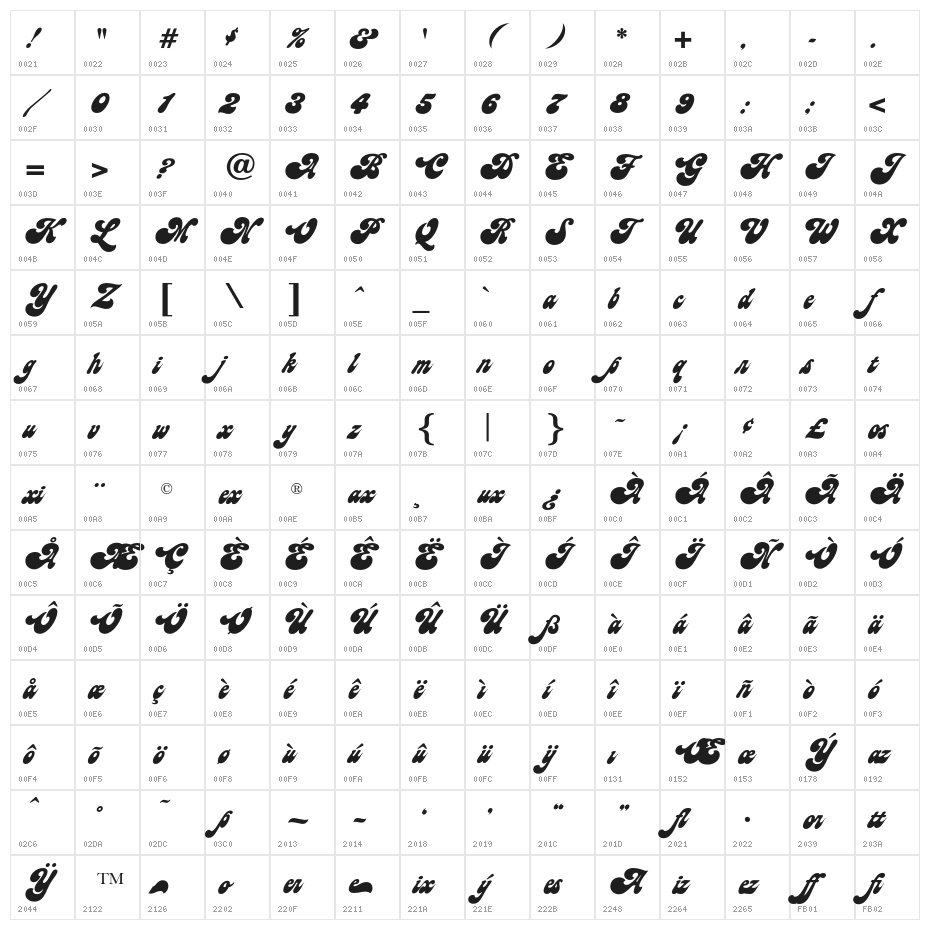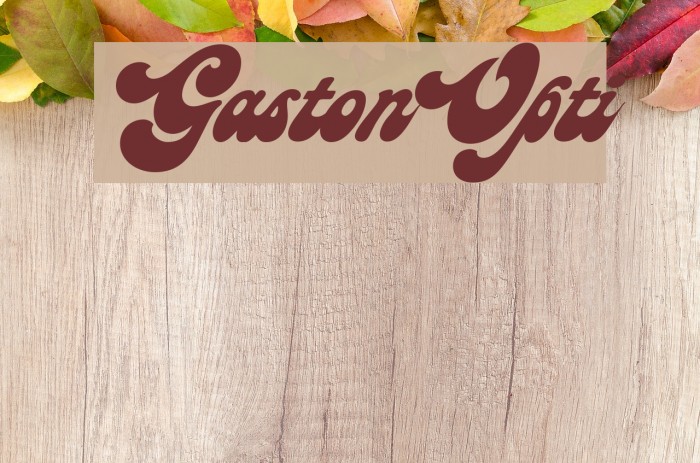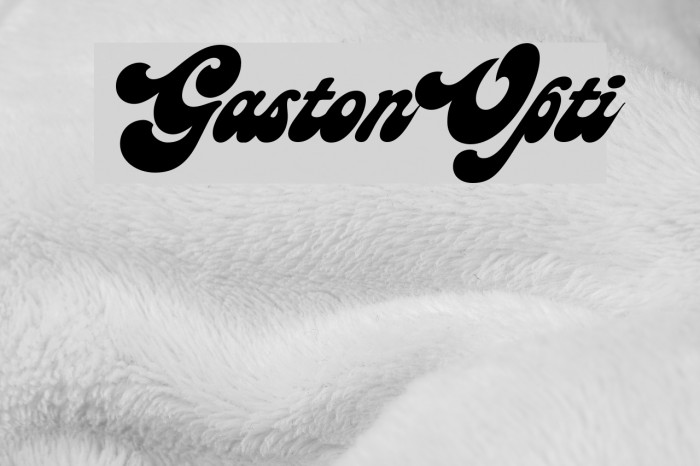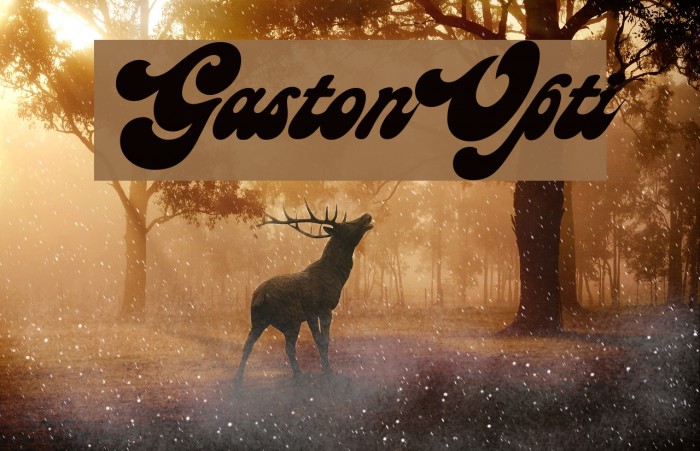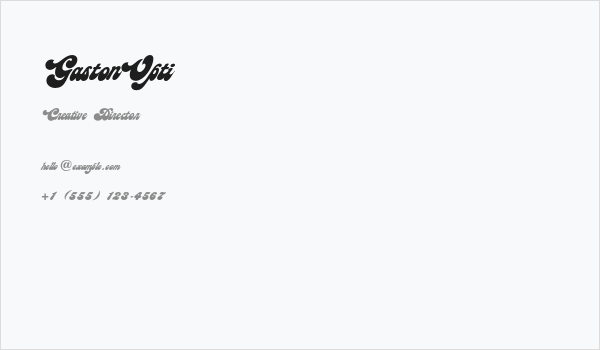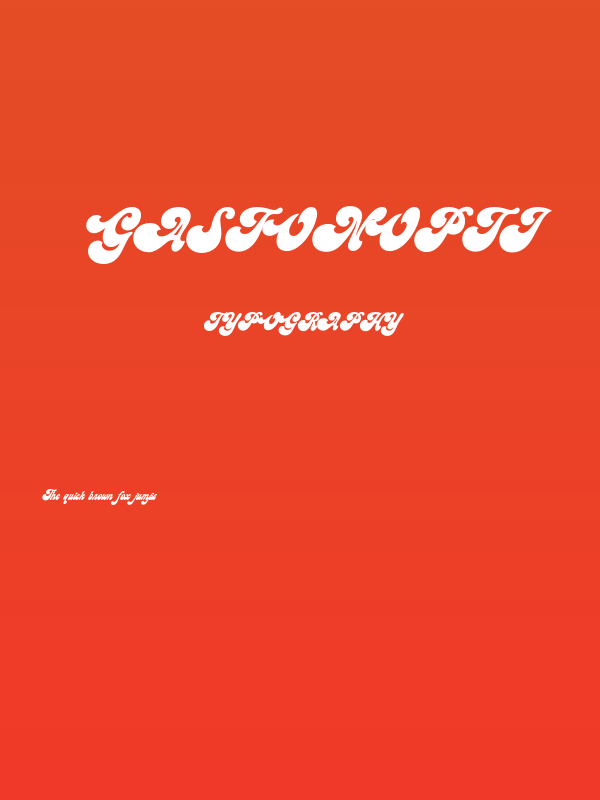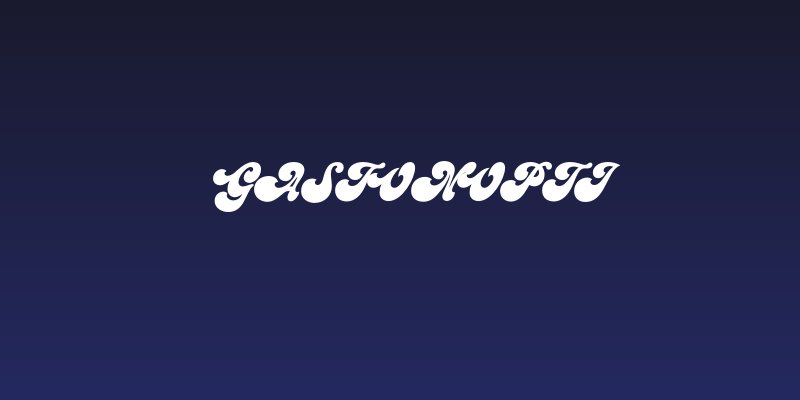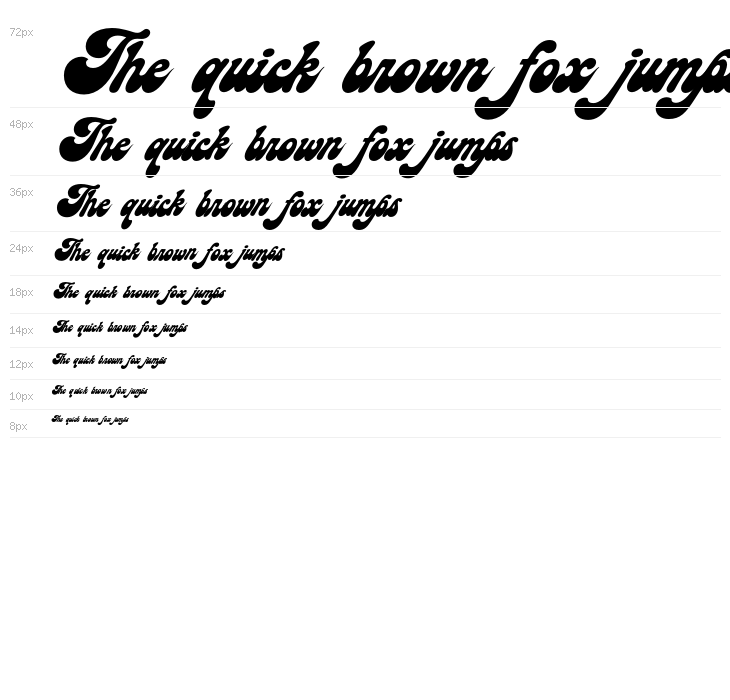
GastonOpti Font
| Caso d'uso | Logos, Headlines, Invitations |
| Progetti proposti | Ideal for branding, logos, invitations, and posters where a bold, artistic touch is desired. |